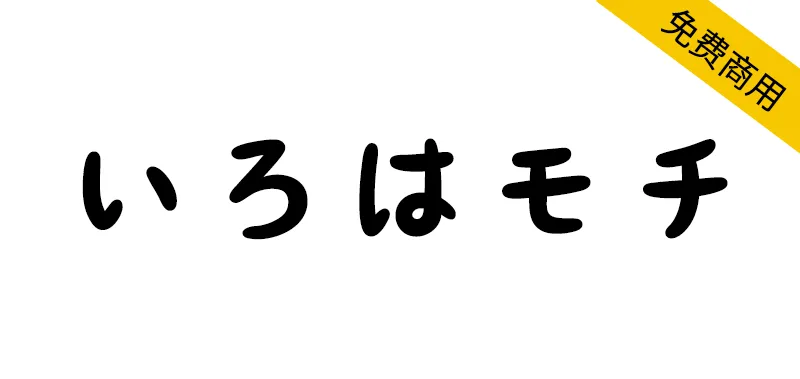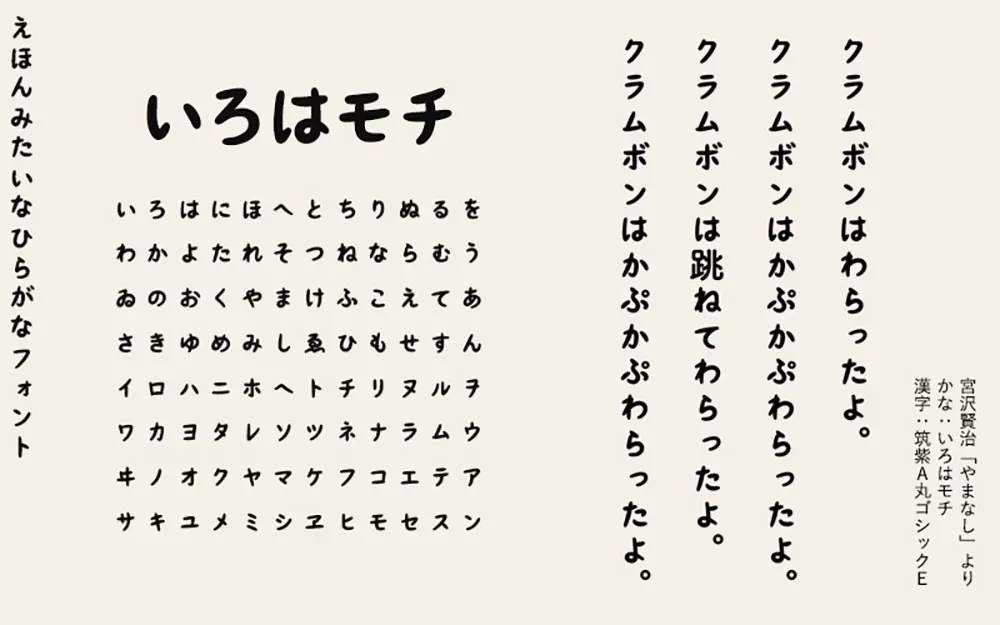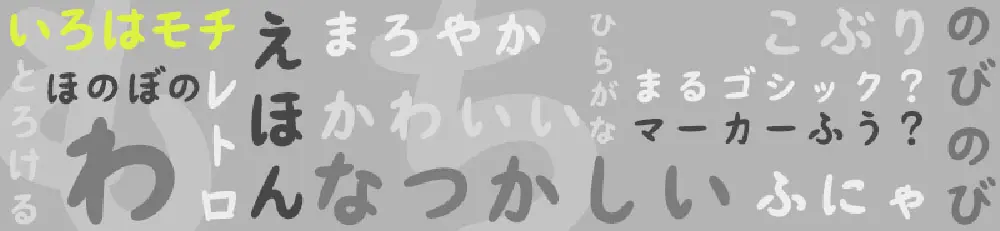
いろはモチ介紹
いろはモチ是一款適合圖畫書的懷舊平假名字體。骨架是以“いろはマル”為原型的,所以有些老套。這是僅適用於平假名和片假名的字體。此外,還包括一些基本的標點符號(標點符號、括號等符號)。
絵本に合いそうな懐かしい感じのひらがなフォントです。骨格は『いろはマル』をベースにしたのでなんとなくオールド寄り。ひらがな・カタカナのみのフォントです。おまけでいくつか基本的な約物(句読點や括弧などの記號)も入っています。